[Font] Font Handwritting
Hừm, chào mình nữa đây. Như các bạn yêu cầu, mình sẽ share font handwritting, trong 2 font dưới đây phiền các bạn chọn 1 trong 2 nha.
[1]
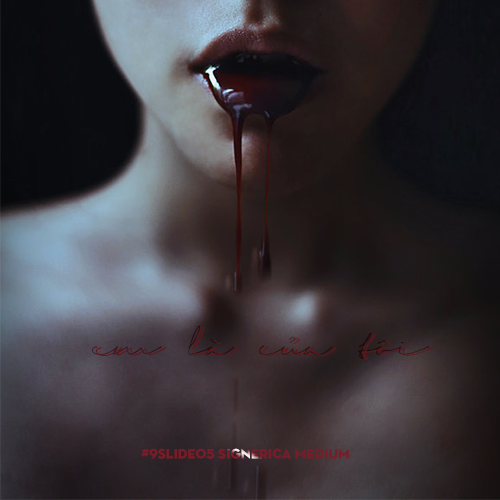
Giờ mới để ý để text chính chìm vcl =)))) để cap cho các bạn nhìn kĩ hơn =))Mình thích font này vcl =)))))
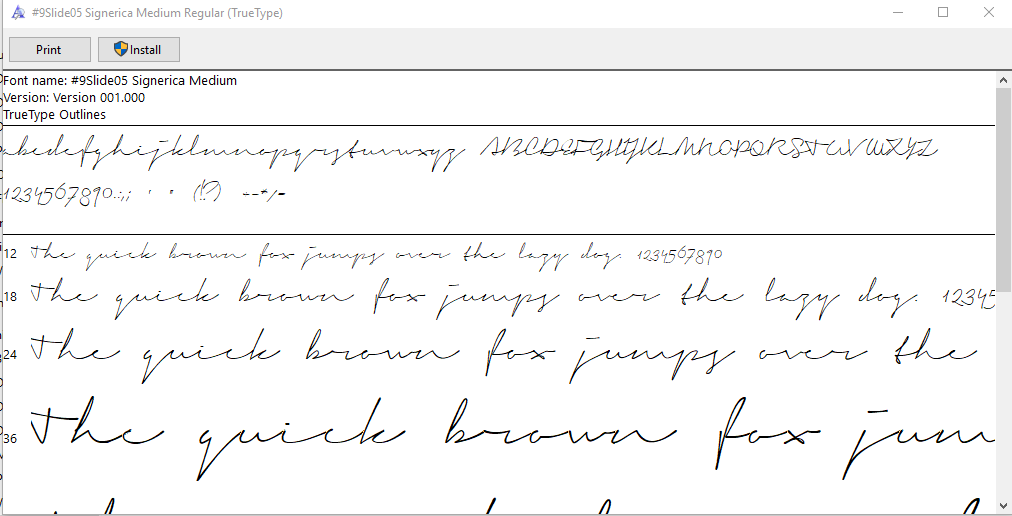
[2]